25+ Font Chữ Miễn Phí Đẹp Nhất Cho Website
Một phần quan trọng của việc truyền đạt thông điệp và nội dung là font chữ. Sử dụng font chữ miễn phí đẹp và phù hợp khi thiết kế website giúp nâng cao tính thẩm mỹ của website, làm cho nội dung dễ đọc hơn và thu hút người xem. Hôm nay, Terus sẽ tổng hợp 25 font chữ miễn phí đẹp nhất cho thiết kế website.
I. Tổng hợp các loại font chữ miễn phí
Việc lựa chọn font chữ miễn phí Việt phù hợp đóng vai trò quan trọng trong thiết kế, giúp truyền tải thông điệp và tạo ấn tượng thị giác hiệu quả. Dưới đây là tổng hợp các loại font chữ miễn phí phổ biến và được ưa chuộng trong năm 2024, được phân loại theo kiểu dáng:
1. Arial
Arial là một font chữ miễn phí phổ biến được sử dụng rộng rãi trong thiết kế web vì nó đơn giản và dễ đọc. Là một loại font Sans Serif, loại font này thường phù hợp với nhiều lĩnh vực.
Arial, thường được sử dụng thay thế cho các font khác, là một lựa chọn tuyệt vời cho các website với nhiều hệ điều hành. Điều này đặc biệt đúng đối với Windows, nơi Arial thường được sử dụng để thay thế cho các font khác.
2. Times New Roman
Trong danh sách các font chữ miễn phí đẹp, Times New Roman là một phần không thể thiếu. Phần lớn mọi người quen thuộc với font này, đặc biệt là những người đã từng sử dụng các công cụ soạn thảo văn bản.
Font Windows thường là Times New Roman. Các trang báo, nội dung văn bản trong tài liệu và nhiều ứng dụng khác có thể sử dụng loại font này.
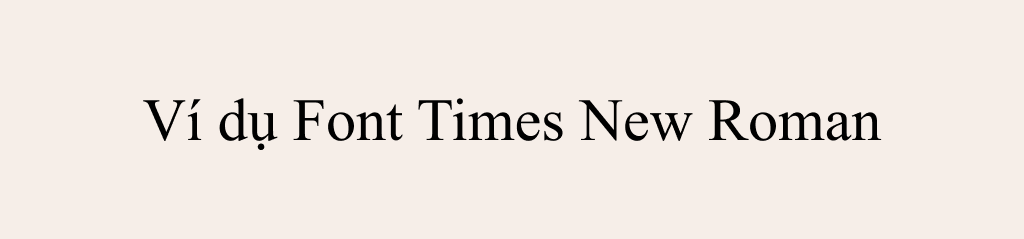
3. Helvetica
Font sans serif Helvetica có chiều cao đều và khoảng cách giữa các ký tự gần nhau. Do đó, font chữ miễn phí Helvetica phù hợp với các kích thước chữ nhỏ mà vẫn giữ cho người xem dễ đọc.
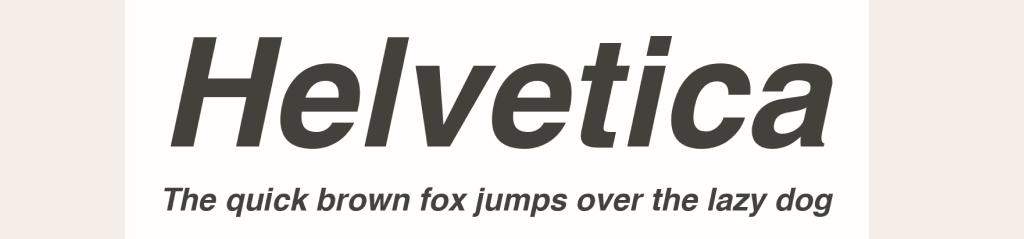
4. Courier New
Courier New là một font chữ miễn phí hấp dẫn và phổ biến. Vì nó giống với Times New Roman, font chữ này thường được ưa chuộng trong các ứng dụng soạn thảo văn bản. Khi bạn muốn làm nổi bật một phần cụ thể trong nội dung, Font Courier New là lựa chọn tuyệt vời.
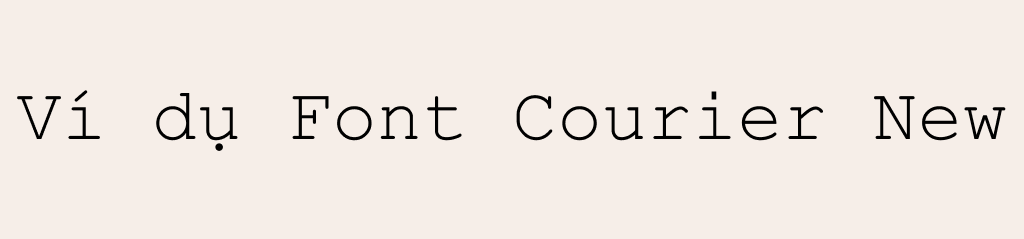
5. Verdana
Font chữ miễn phí Verdana đơn giản và dễ đọc. Đây là một font chữ phổ biến để sử dụng trong thiết kế menu của nhà hàng, thường có kích thước trung bình hoặc nhỏ. Nếu bạn chưa quen với việc tạo menu cho website, bạn có thể học cách sử dụng WordPess để tạo menu.
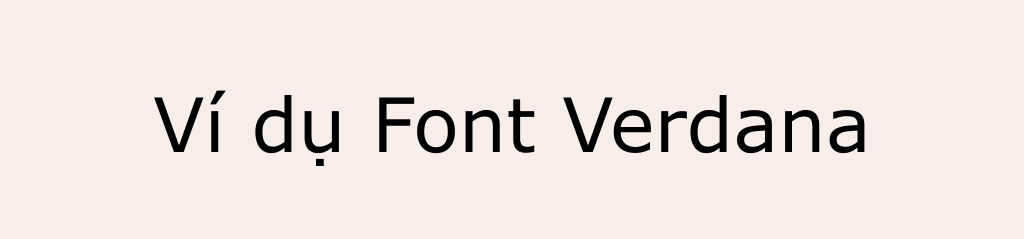
6. Georgia
Font chữ miễn phí Georgia có số ký tự lớn hơn so với các font khác. Do đó, Georgia được sử dụng thường xuyên trong các tình huống đặc biệt.
Khi trình bày văn bản, Georgia được coi là một font tiếng Việt đẹp và phổ biến. Không sử dụng Georgia cùng với Times New Roman có thể khiến chữ trông lớn hơn và phức tạp hơn.
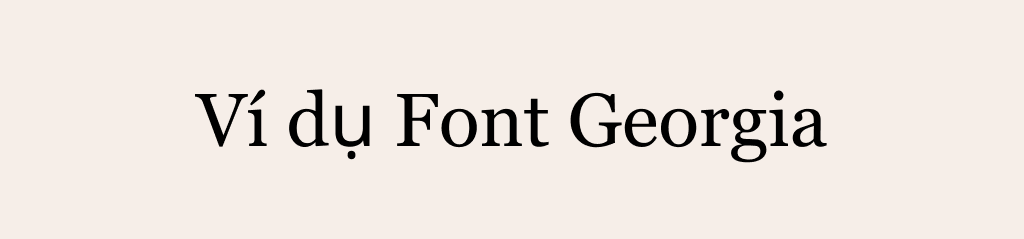
7. Tahoma
Tahoma là một font chữ Tiếng Việt phổ biến để thiết kế website. Website có thiết kế đơn giản, dễ đọc và rõ ràng, giúp nó trở nên hấp dẫn và thu hút người truy cập. Font chữ Tahoma này có thể được sử dụng để thiết kế tờ rơi, bìa hoặc trang trí ngoài việc sử dụng cho nội dung website.
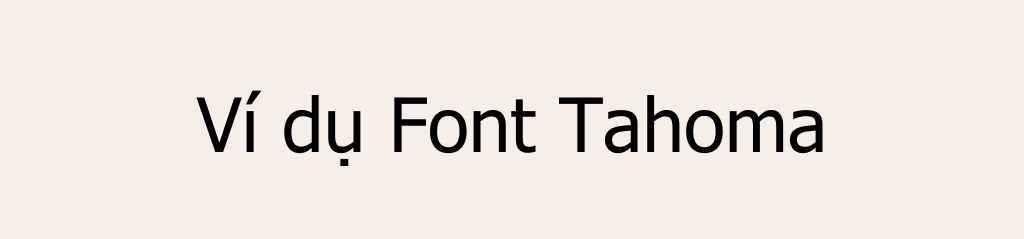
8. Calibri
Một trong những font chữ Tiếng Việt phổ biến và đẹp nhất là Calibri. Các ứng dụng soạn thảo văn bản như Microsoft Word thường sử dụng nó làm mặc định. Calibri có kiểu chữ đơn giản và sang trọng, và nó phù hợp với nhiều loại nội dung trên internet, đặc biệt là nội dung có kích thước chữ từ 12pt trở lên.
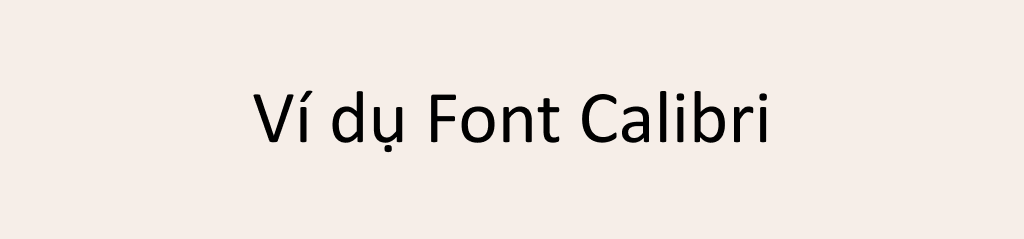
9. Garamond
Thông thường được sử dụng trong giáo dục, font chữ miễn phí Garamond có sẵn trên hệ điều hành Windows. Garamond là một trong những font chữ phổ biến nhất nhờ hình thức dễ đọc và sự đa dạng trong thiết kế.
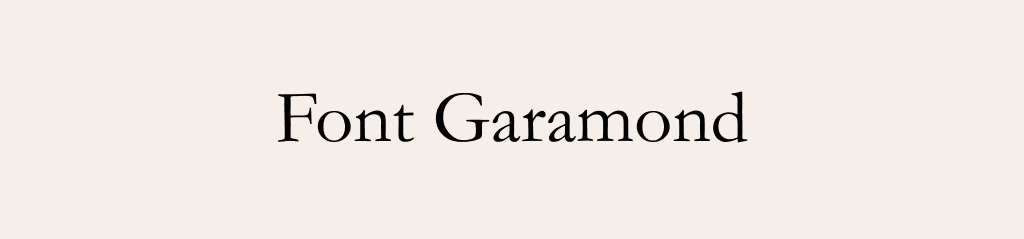
10. Bookman
Khi bạn cần văn bản có kích thước nhỏ, font chữ miễn phí Bookman rất hữu ích, đặc biệt là đối với tiêu đề bài viết, bài báo hoặc thông tin tin tức.
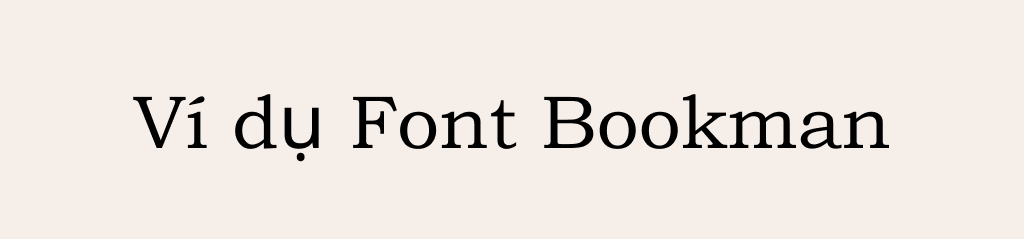
11. Museo Moderno
Museo Moderno có kiểu dáng hình học thanh lịch. Nó sử dụng các đường nét tròn hiện đại và đơn giản. Lấy cảm hứng từ các phong trào nghệ thuật tiên phong ở châu Âu vào đầu thế kỷ 20, font chữ Tiếng Việt này tạo nên một kiểu chữ đặc biệt, đơn giản nhưng hấp dẫn.
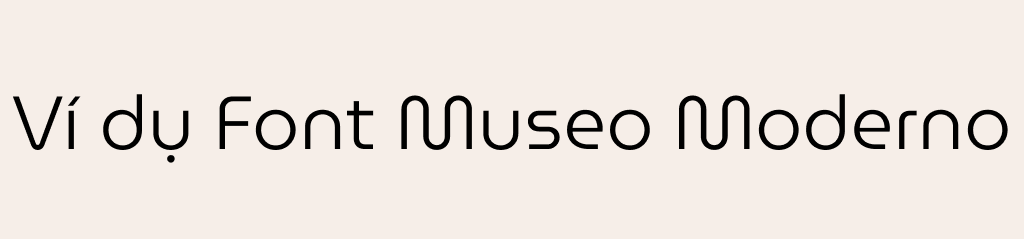
12. Pacifico
Lấy cảm hứng từ văn hóa lướt sóng của Mỹ vào thập kỷ 1950, font chữ Tiếng Việt Pacifico sử dụng nét bút lông độc đáo để viết. Nét chữ tròn trịa của Pacifico mang đến cảm giác thoải mái, mềm mại và không quá cầu kỳ.
13. Roboto
Roboto là một bộ font chữ Tiếng Việt không có chân được phát triển bởi Google và dễ sử dụng. Bởi vì nó có phong cách hiện đại và linh hoạt, bạn có thể dễ dàng thay đổi độ đậm và độ nhạt của văn bản để phù hợp với nhu cầu của riêng bạn.
14. Dancing Script
Dancing Script là một loại font chữ Tiếng Việt đặc biệt có các đường nét sống động và hơi nghiêng. Một cảm giác mềm mại và lả lướt được tạo ra bởi những nét thanh và đậm trong Dancing Script khiến chữ viết như đang nhảy múa trên trang.
Do đó, Dancing Script được coi là một font chữ trang trí đơn giản nhưng đủ mạnh để gây ấn tượng mạnh mẽ với người xem.
15. Noto Serif
Noto Serif là một loại font chữ Tiếng Việt khá đơn giản. Đây là một font thiết kế đẹp và có độ dày nét và chiều cao khá tương thích để hiển thị trên web ở nhiều ngôn ngữ.
5. Sử dụng font chữ Tiếng Việt có ảnh hưởng đến tốc độ tải website không?
Việc sử dụng font chữ Tiếng Việt có thể ảnh hưởng đến tốc độ tải website, đặc biệt là khi sử dụng các font chữ có nhiều ký tự phức tạp hoặc định dạng đặc biệt. Do đó, bạn nên chọn font chữ được tối ưu hóa cho website và sử dụng các dịch vụ website font như Google Fonts để giảm thiểu ảnh hưởng đến tốc độ tải trang.